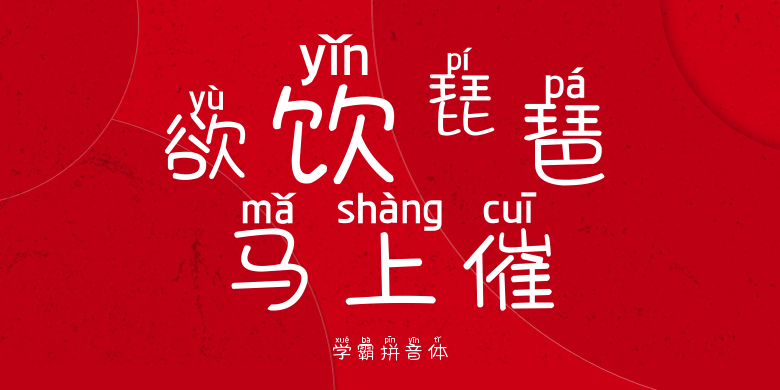
学霸拼音体
学霸拼音体,这款字体结构工整、笔画清晰,兼顾美观与易读性,适用于标题、正文、海报、包装、LOGO 等多种场景。字形优雅稳定,风格百搭耐看,适配日常排版与创意设计,让文字呈现更舒适、更具质感。学霸拼音体一笔一画,皆是细节,以均衡的比例、流畅的线条打造舒适视觉体验,字形端正大气,风格简约现代。无论是商业设计、品牌宣传还是日常排版,都能轻松驾驭,让文字更有格调与力量。学霸拼音体字体下载。